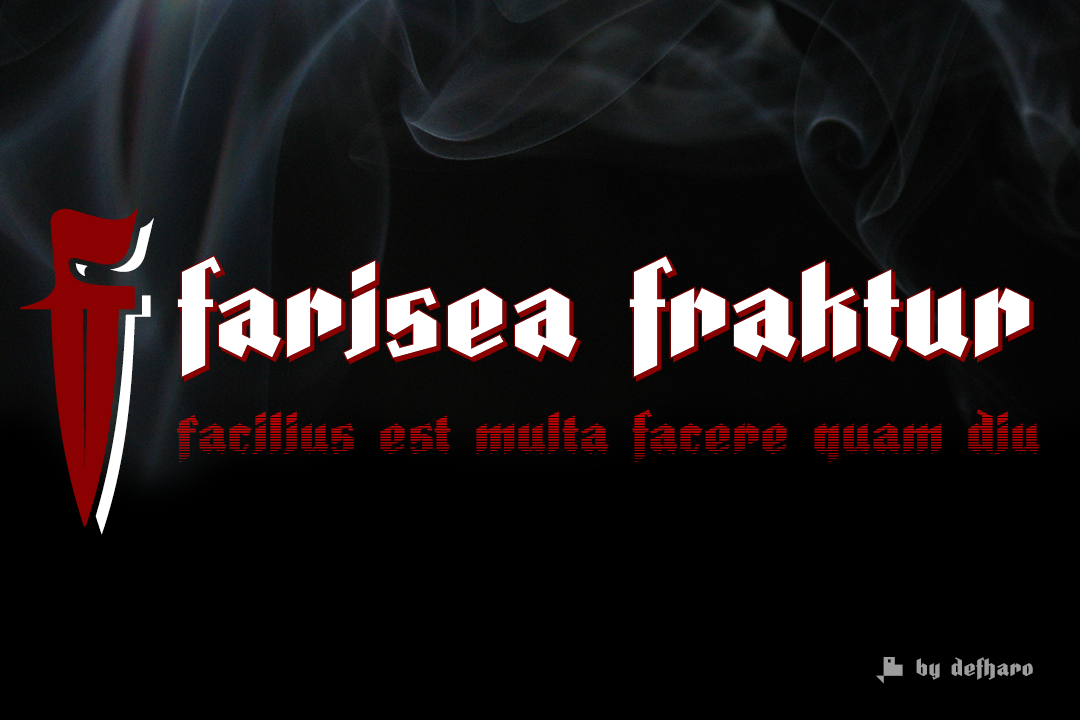
A fonte ‘Farisea Fraktur & Layered Font’ é uma tradução modernizada do estilo typográfico Fraktur, originário dos góticos e popularizado na Alemanha e norte de Europa no início do século XVI. Este tipo de letra é marcado por seus traços grossos e perfil agudo produzido pela caneta. As fontes ‘Farisea Fraktur’ são características por sua forma quadrada, com uma inclinação inicial de 64 graus para as finais superiores e inferiores. Elas ganham destaque devido à forte contraste entre as partes que parecem antenas, resultando em um x grande e alto o suficiente para garantir a proporção quadrada da fonte. Esta é uma opção perfeita para aqueles buscando personalizar seu design com um estilo clássico e elegante, sem se distanciar do aspecto tradicional dos Frakturs.